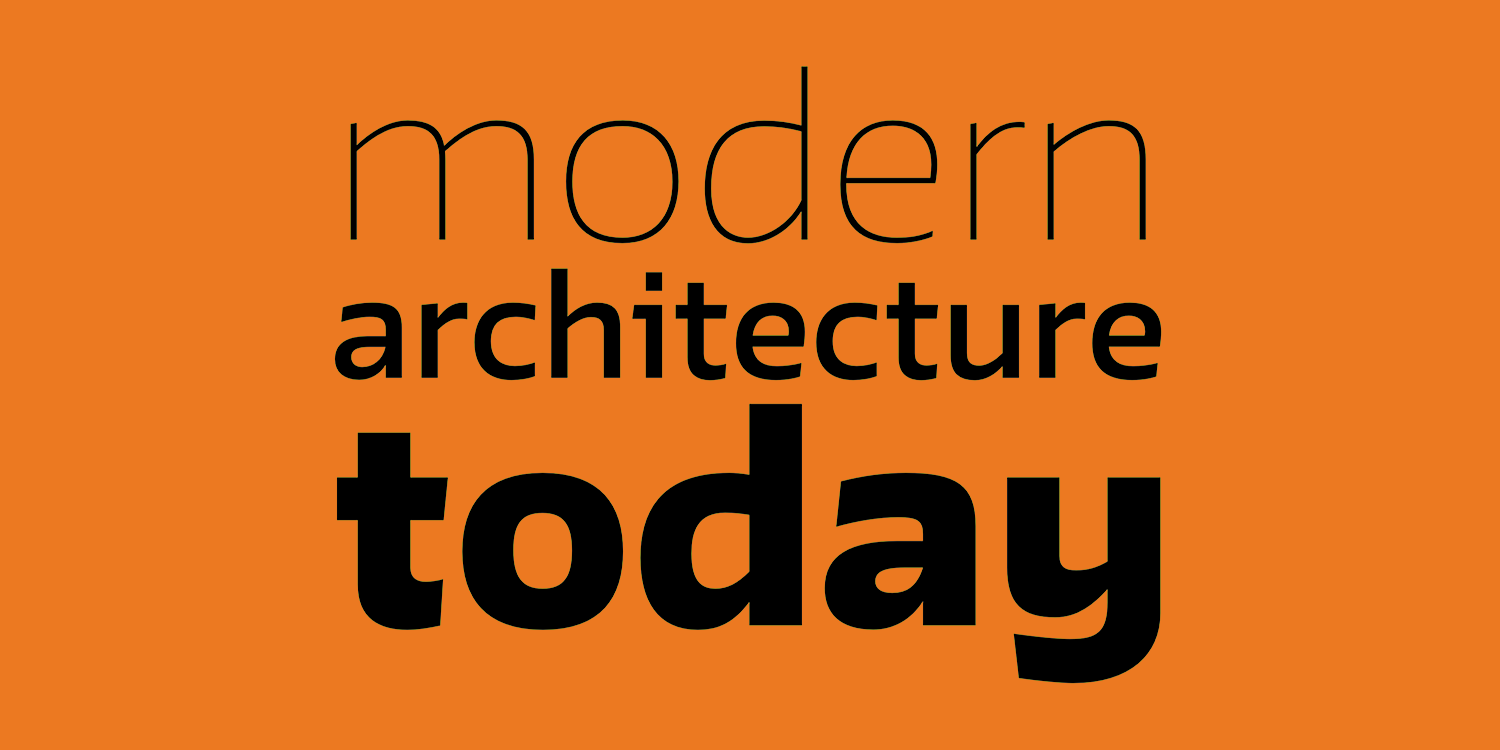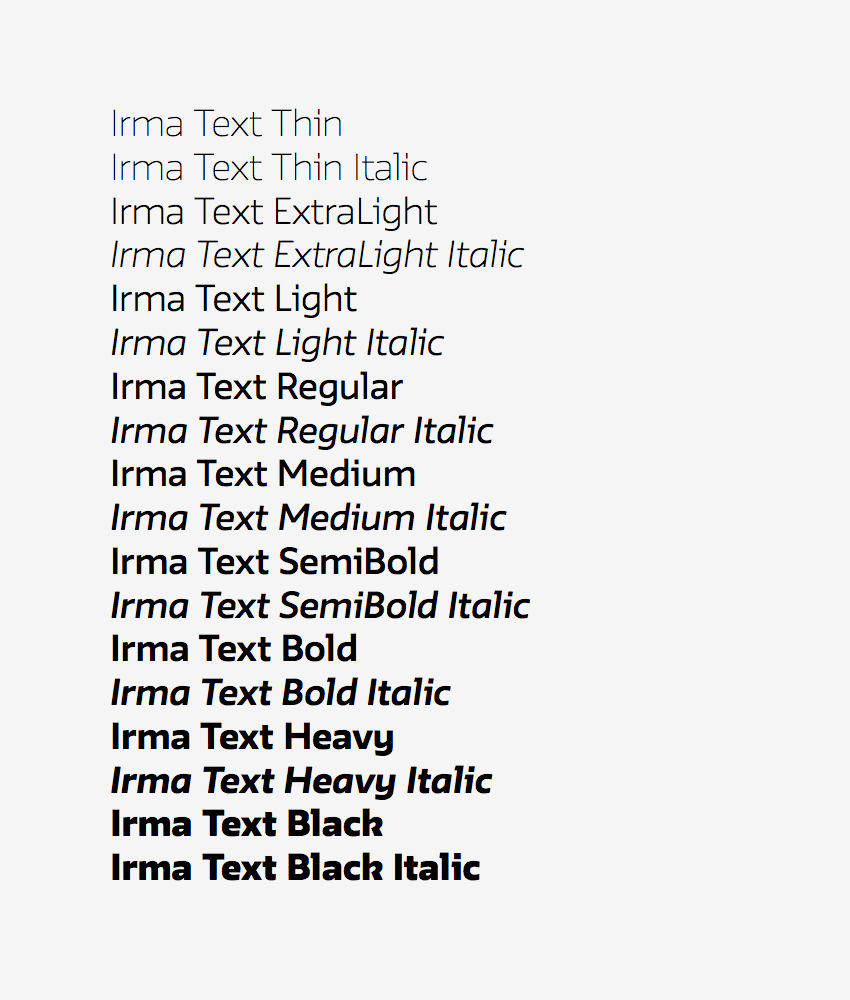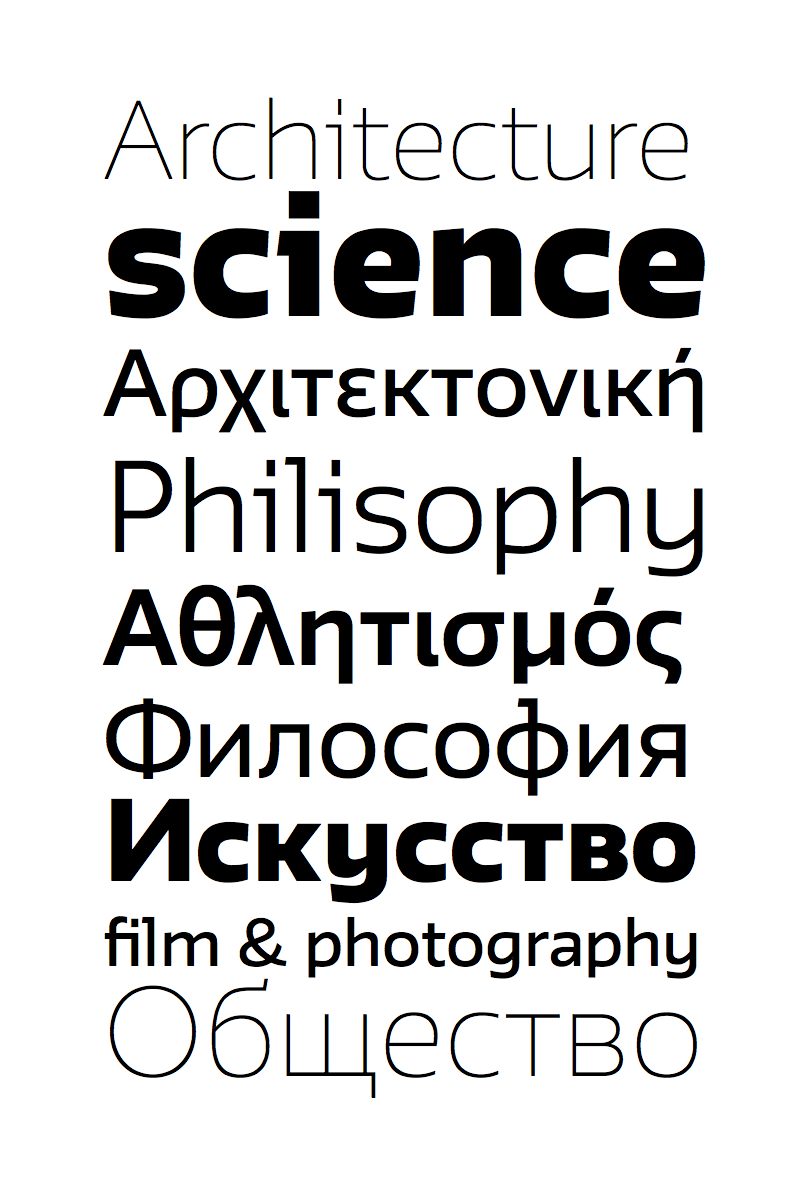
Irma Text ist eine serifenlose Textschrift, bei der zwei Konstruktionsprinzipien miteinander vereint wurden: zum einen enthält sie geometrische, zum anderen handschriftliche Elemente. Diese Synthese verleiht ihr einen technisch-dynamischen Charakter.
Irma Text ist Mitglied der Irma-Schriftsippe, welche außerdem eine bildschirmoptimierte Version (Irma Screen), eine Egyptienne (Irma Slab) sowie eine abgerundete Sans (Irma Round) beinhaltet. Irma Text liegt in zwei Weiten (Standard, Narrow) vor und enthält neben dem lateinischen ebenso ein griechisches (polytonisch) sowie ein kyrillisches Alphabet. Zahlreiche Opentype-Features ergänzen ihre gute Ausstattung.